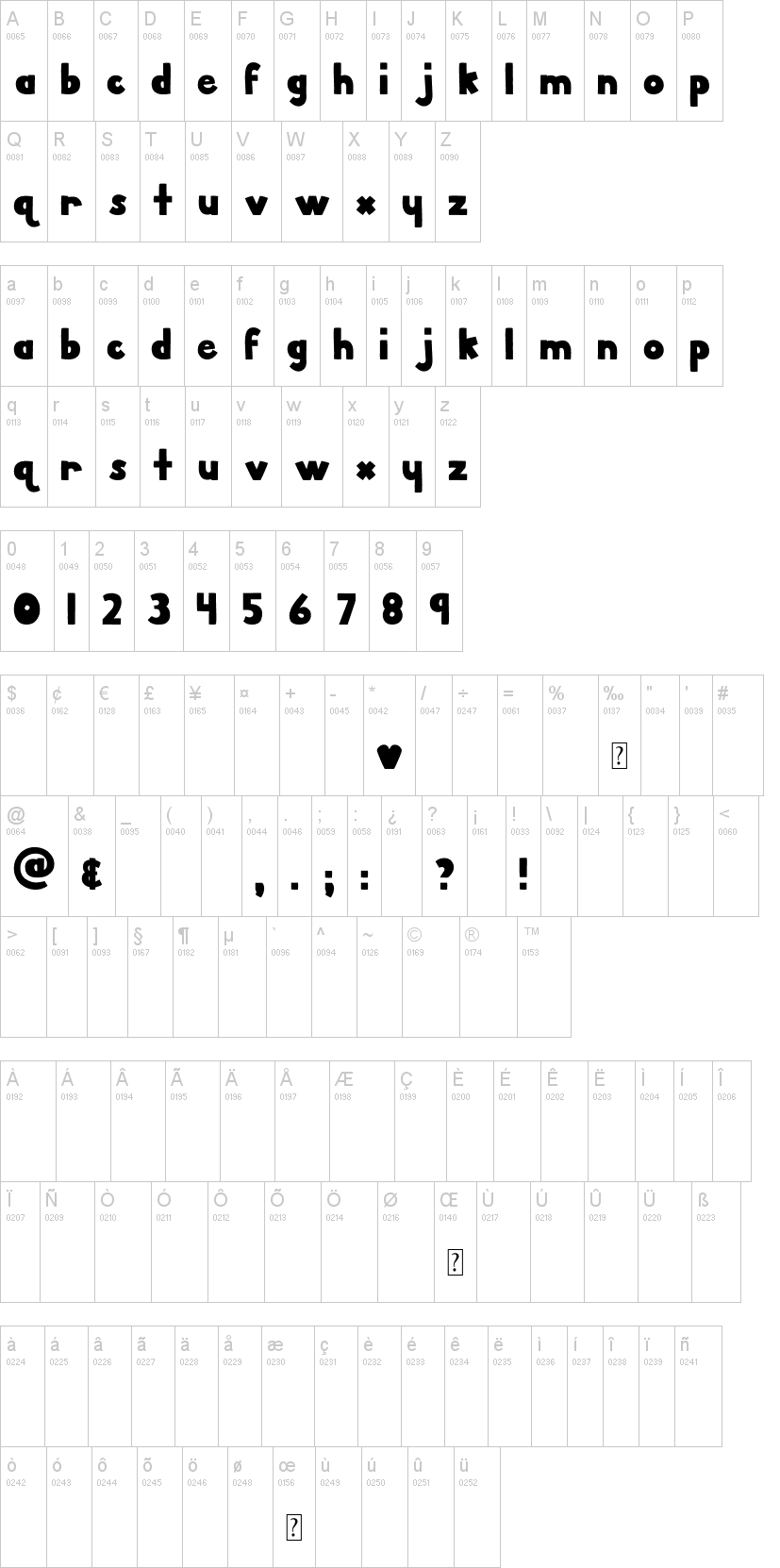
MTF Pork Chop
? MTF Pork Chop字体是由MyFonts出品的一款手写字体。该字体拥有具有柔和、温暖的特点,是一款非常适合用于浪漫、可爱、温馨的场景中的字体。它具有优美的笔画,更有助于渲染出温暖、浪漫的氛围,是一款非常适合用于婚礼、婚礼邀请函等场景的字体。
MTF Pork Chop是一款非常不错的手写艺术字体,具有很好的视觉感,适合于文化类的宣传设计、商业类品牌的广告和产品包装设计以及个性化文字排版等较多场景。
MTF Pork Chop字符映射图